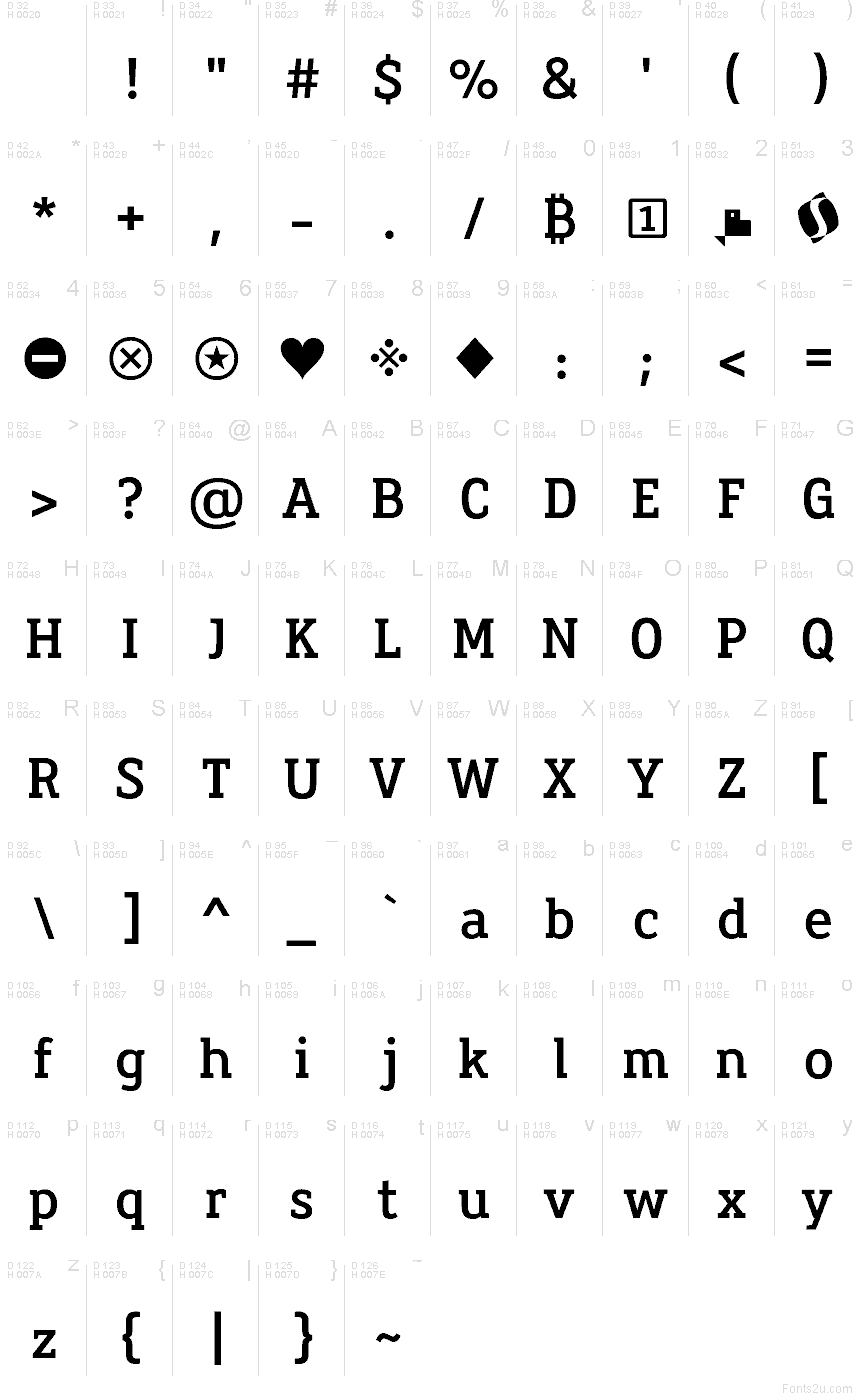
Biotrip Serif Medium
A Biotrip Serif, da deFharo, é uma fonte serifada gratuita definida por serifas retangulares largas e um ritmo firme e vertical que confere às letras uma presença marcante, quase como num cartaz. A repetição dos seus pés maciços, curvas redondas e junções planas tornam-na deliberada e estruturada, em vez de ornamental ou tradicional.
Essa estrutura confere ao texto curto um papel de destaque no branding, cabeçalhos editoriais, embalagens, capas de álbuns e títulos, onde o detalhe das serifas exige um peso gráfico real. A Biotrip Serif também é excelente para logotipos e merchandising, pois as suas terminações horizontais largas criam uma silhueta sólida que se mantém coesa em palavras compactas e layouts empilhados.
Biotrip Serif is a friendly typeface family that is, above all, a journey. A journey (Trip) from the purity of geometry to the warmth of the organic (Bio).
Biotrip Serif comprises 14 methodically designed fonts, distributed across 2 styles (Regular and a genuine, flowing Italic) and 7 weights, ranging from the ethereal elegance of Light to the powerful impact of Black.